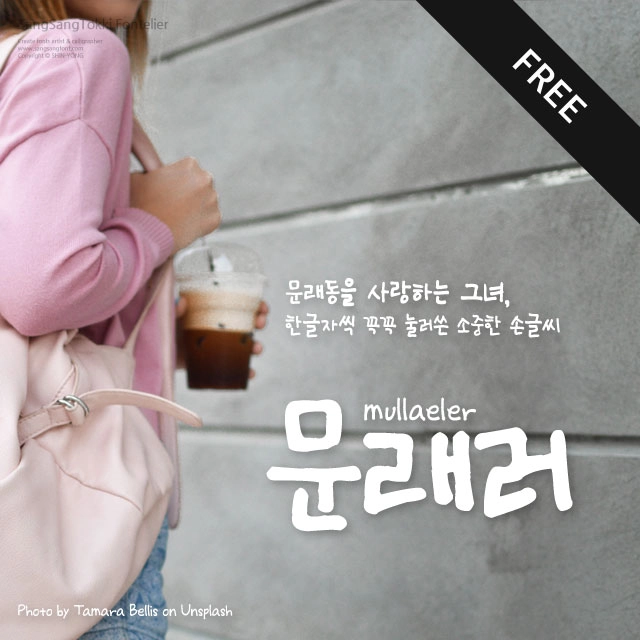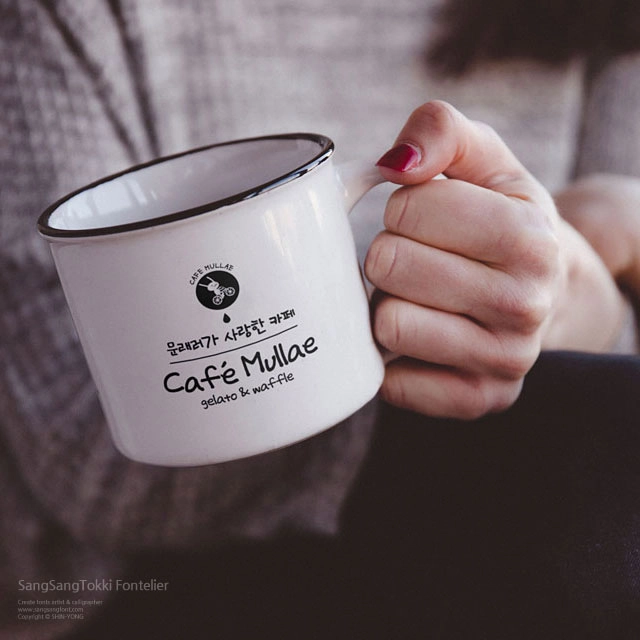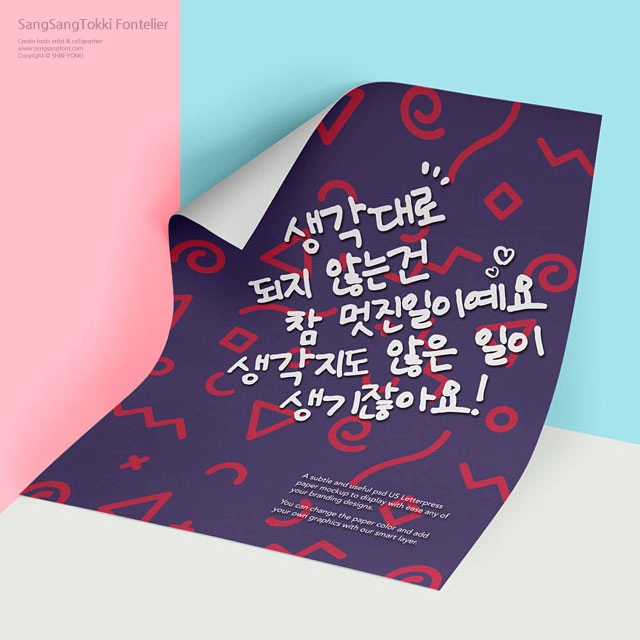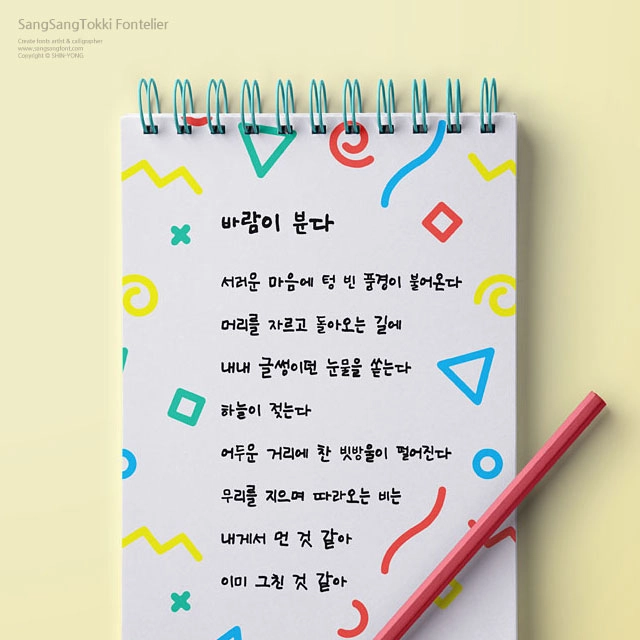
문래러
문래동을 사랑하는 그녀가 한글자씩 꼭꼭 눌러쓴 손글씨, 문래러!
문래동을 사랑하는 그녀의 깜찍한 손글씨 <문래러>는 상상토끼 용이 작가의 대한민국 1인1폰트 네번째 주인공인 수진님의 손글씨를 기초로 해서 만들어진 폰트입니다. 소중한 글씨로 멋진 폰트를 만들게 허락해준 수진님께 감사의 마음을 전합니다. |